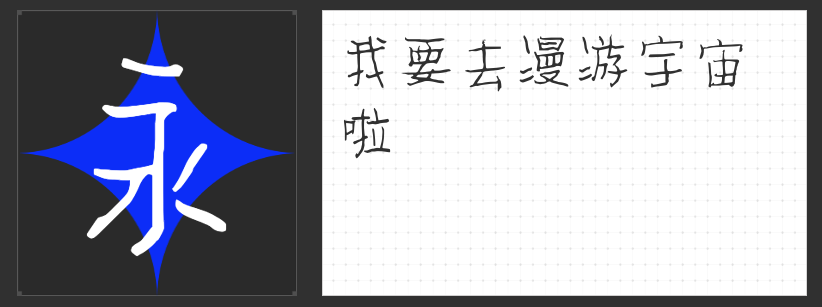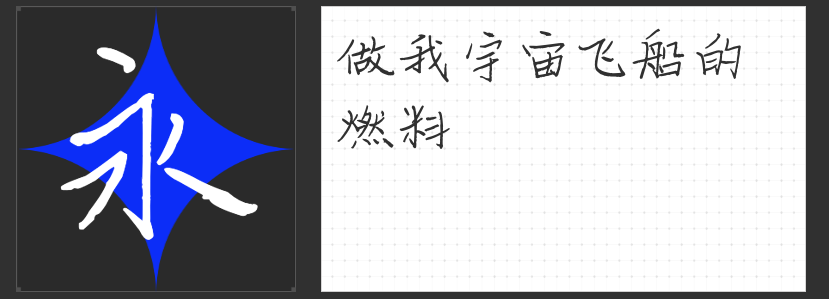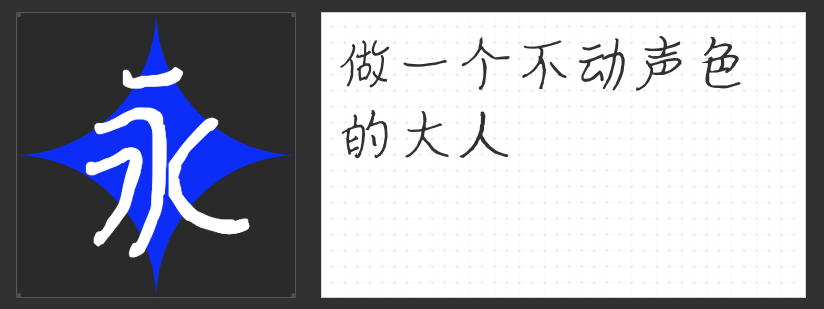
让文字拥抱温柔时光:清新治愈手写字体推荐
在这个快节奏的数字时代,寻找一抹能温柔触动心弦的清新笔触,成为了许多人生活中的小确幸。今天,就让我们一起漫步于手写字的字海,探索既治愈又别具一格的手写字库字体,它们如同春日里的一缕轻风,拂去心头的尘埃。
MyFont冲鸭简繁:这款字体以其独特的活泼姿态跃然屏上,设计上不仅满足了多元文化的需求,更在字里行间透露出一种积极向上的力量感。“冲鸭”二字仿佛自带萌态,是日记、手账或是温馨提醒的最佳伴侣。
MyFont凌渡哥哥简:若说有一种字体能温柔地包裹你的心房,那非MyFont凌渡哥哥简莫属。它的每一笔一划都透露着成熟与稳重,又不失亲切与温暖,如同一位老朋友在你耳边轻声细语。这款字体适合书写那些需要深度与温度的文字,无论是散文随笔还是情感寄语,都能完美诠释。
MyFont濑户风车简:想象一下,海风轻拂,风车缓缓转动,那份宁静与和谐正是濑户风车简带给我们的感受。MyFont濑户风车简线条流畅,结构均衡,带有一丝日式简约的韵味,让人仿佛置身于宁静的海边小镇。它适合用于旅游笔记、咖啡馆菜单或是任何希望营造轻松愉悦氛围的文本设计。
MyFont濑户人鱼简:如果说濑户风车简是海边的宁静,那么濑户人鱼简则是深海中的神秘与梦幻。MyFont濑户人鱼简融入了人鱼传说的浪漫元素,每一个字都像是从古老传说中流淌而出,充满了故事感与想象力。它适合用于绘本、艺术展览的介绍或是任何需要增添神秘色彩的设计中。
四款手写字体,四种风情,它们以各自独特的方式,在数字世界中构建起一座座清新治愈的桥梁,连接着每一个渴望美好与温柔的心灵。选择一款,让文字成为你表达情感、记录生活的最佳媒介吧。